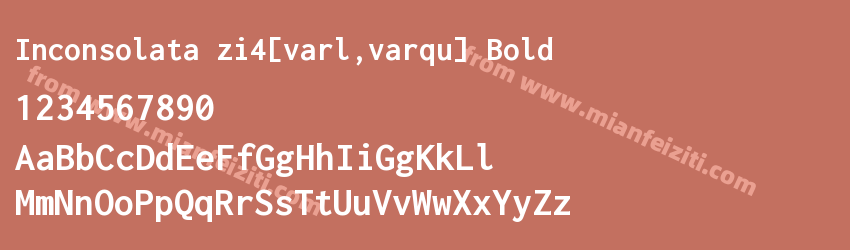
![Inconsolata zi4[varl,varqu] Bold Inconsolata zi4[varl,varqu] Bold](https://mimg.cdn.bcebos.com/upload/fontimgs/cover_ogimage/cover_ogimage_391985.png?auth_key=1754109407-0-0-4d85b2c8ac06cff6cce5f57a9c56b5f8)
![Inconsolata zi4[varl,varqu] Bold预览图1 Inconsolata zi4[varl,varqu] Bold预览图1](https://mimg.cdn.bcebos.com/upload/fontimgs/font_image/font_image_391985.png?auth_key=1754109407-0-0-c9d7256396d6bdbdb1f54d1fe26f27f3)
本款“Inconsolata zi4[varl,varqu] Bold”是一款书写很新颖的字体,字体大方,适合各种设计作品使用!欢迎下载!